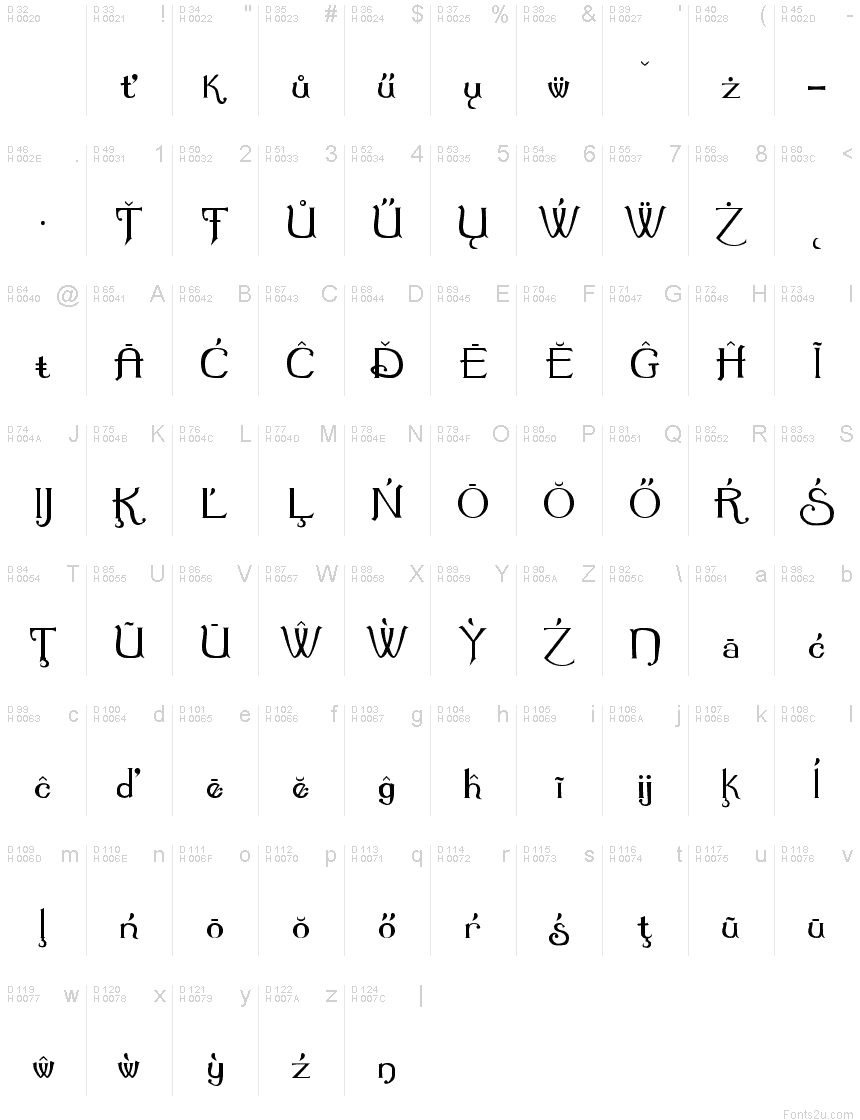
Summertime Extra Characters
Summertime Extra Characters to darmowy, fantazyjny krój pisma w stylu kaligraficznym, przywodzący na myśl ilustracje z bajek. Litery wyróżniają się długimi, wijącymi się liniami i detalami w kształcie łezek, łącząc eleganckie pionowe kreski z luźnymi zawijasami – dzięki temu font jest ozdobny, ale nie traci lekkości.
Świetnie sprawdzi się na zaproszeniach, w brandingu butików, na okładkach książek, w menu kawiarni czy na wizytówkach, gdzie nuta staroświeckiego uroku dodaje całości charakteru. Jako darmowy font, doskonale nadaje się też do krótkich nagłówków, inicjałów i ozdobnych logotypów, ponieważ pętelkowe zakończenia i akcentowane detale robią największe wrażenie w krótkich formach.